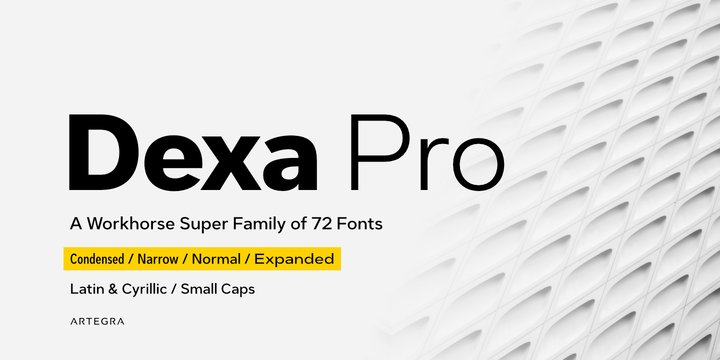
Dexa Pro была спроектирована Джейхуном Биринчи в 2020 году с вдохновением для создания современной супер-семьи, вдохновленной классическими семействами без засечек. Это семейство рабочих лошадей, состоящее из 72 шрифтов в конденсированной, узкой, нормальной и расширенной ширине. Каждая ширина имеет 18 шрифтов от тонкого до черного веса, наряду с их истинно курсивными аналогами. Имея более 770 глифов на шрифт, она предлагает тонну языковой поддержки от всех латинских языков до кириллицы.
Особенности OpenType: маленькие шапки, от шапки до маленькой шапки, альтернативные варианты, фигуры старого стиля, табличная подкладка, табличная подкладка старого стиля, языковые локализации, лигатуры, суперскрипт, подскрипт, числители, знаменатели, дроби, исторические формы.